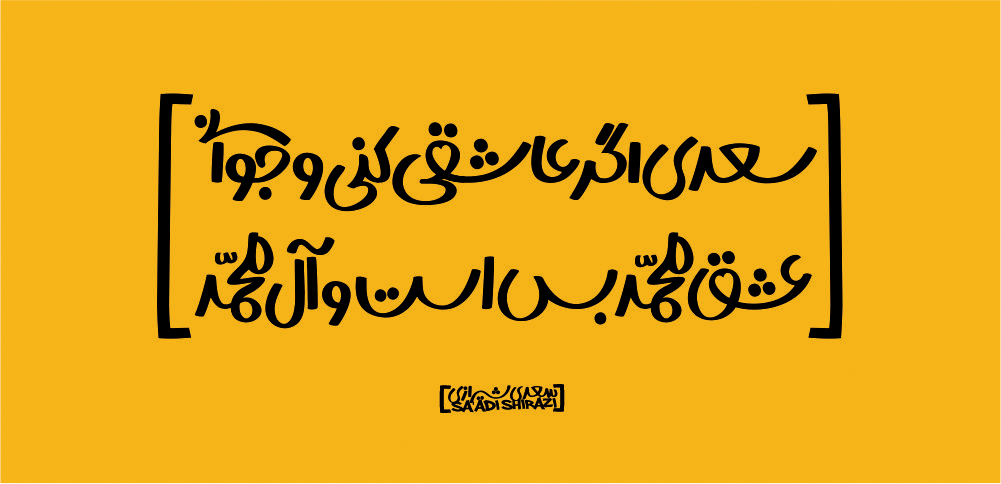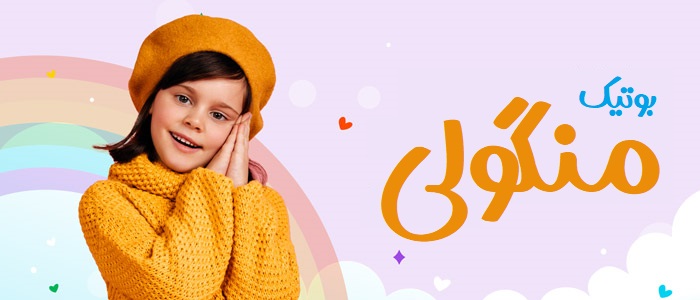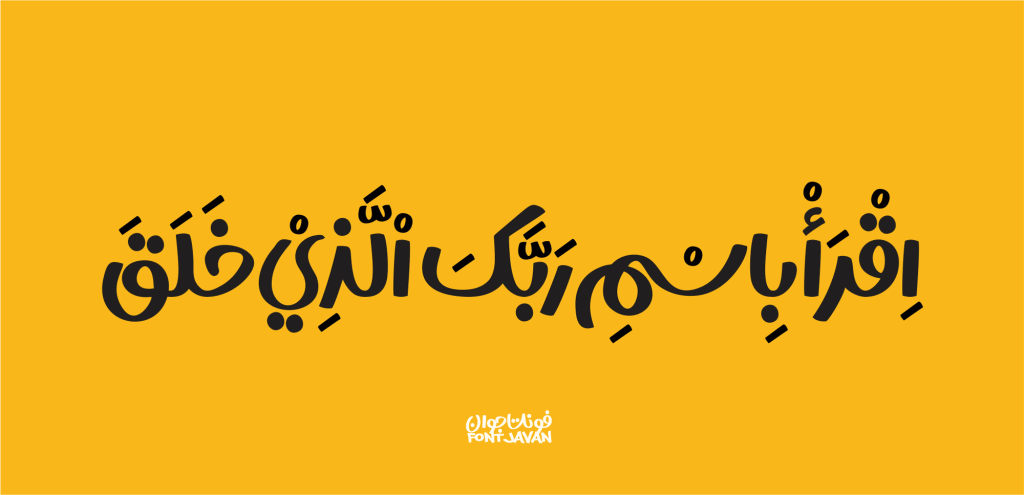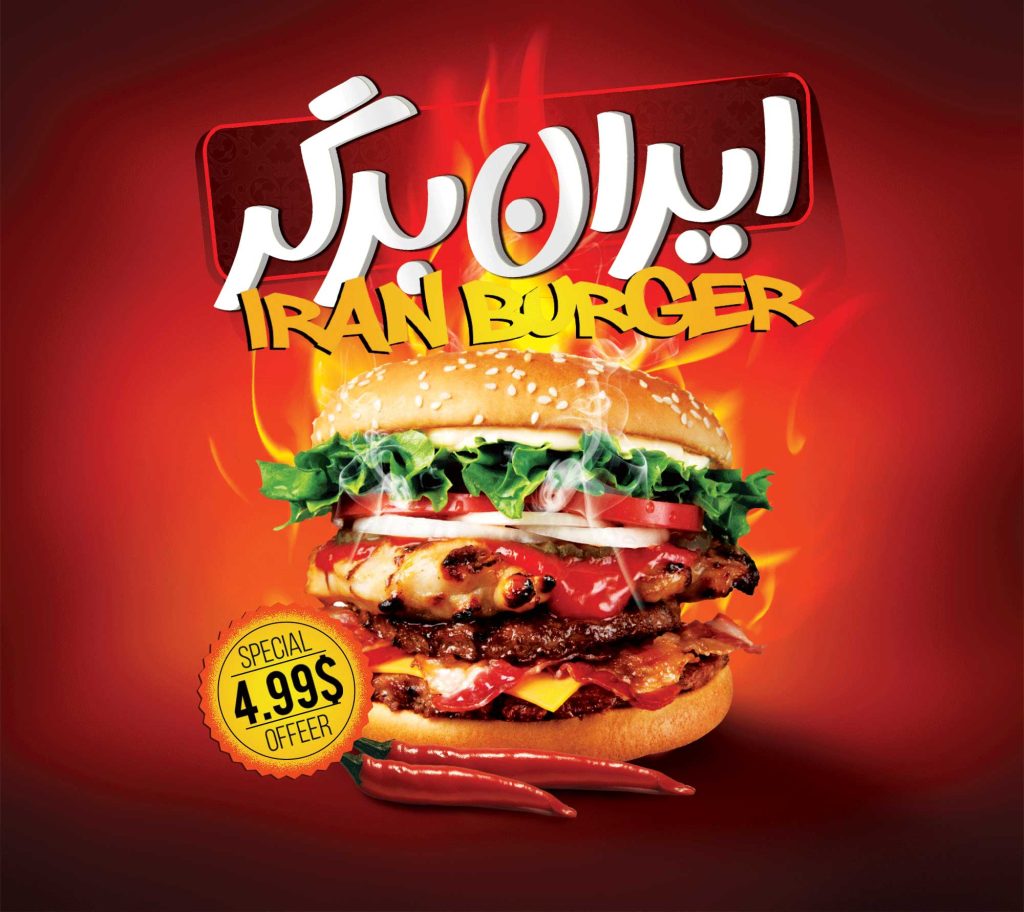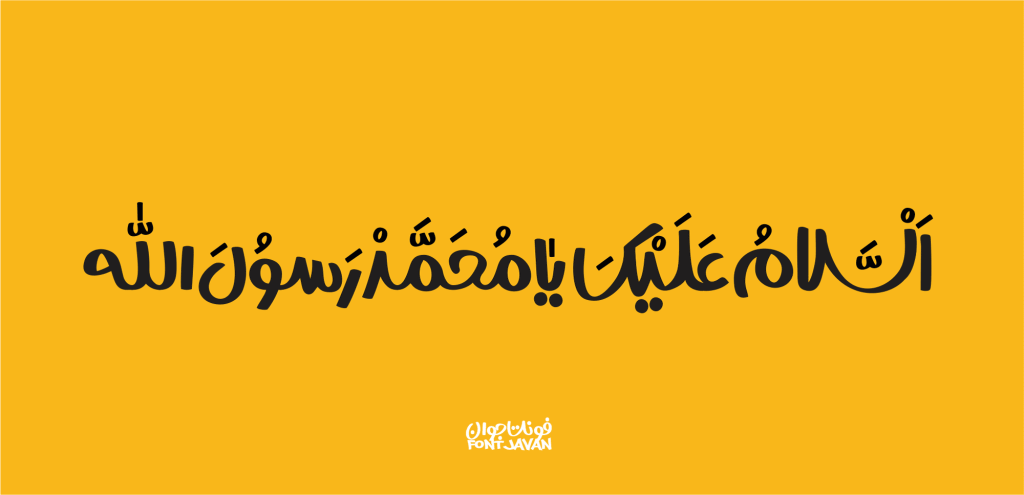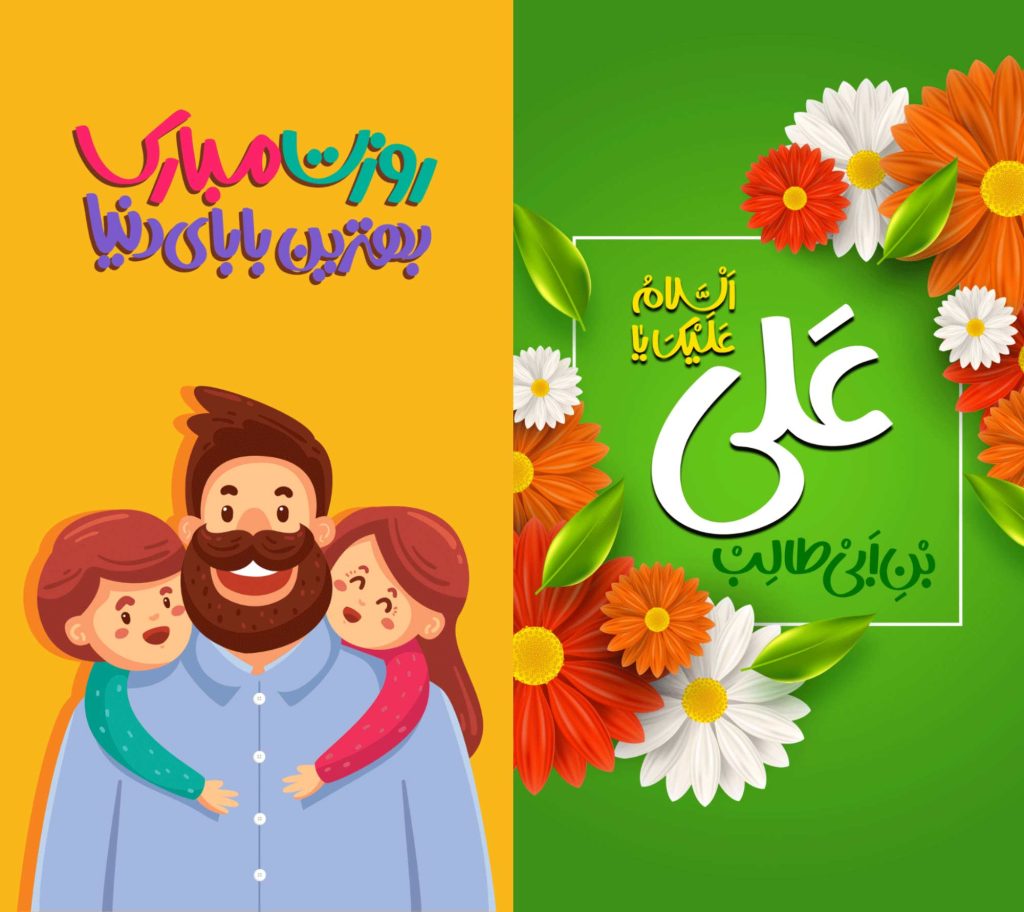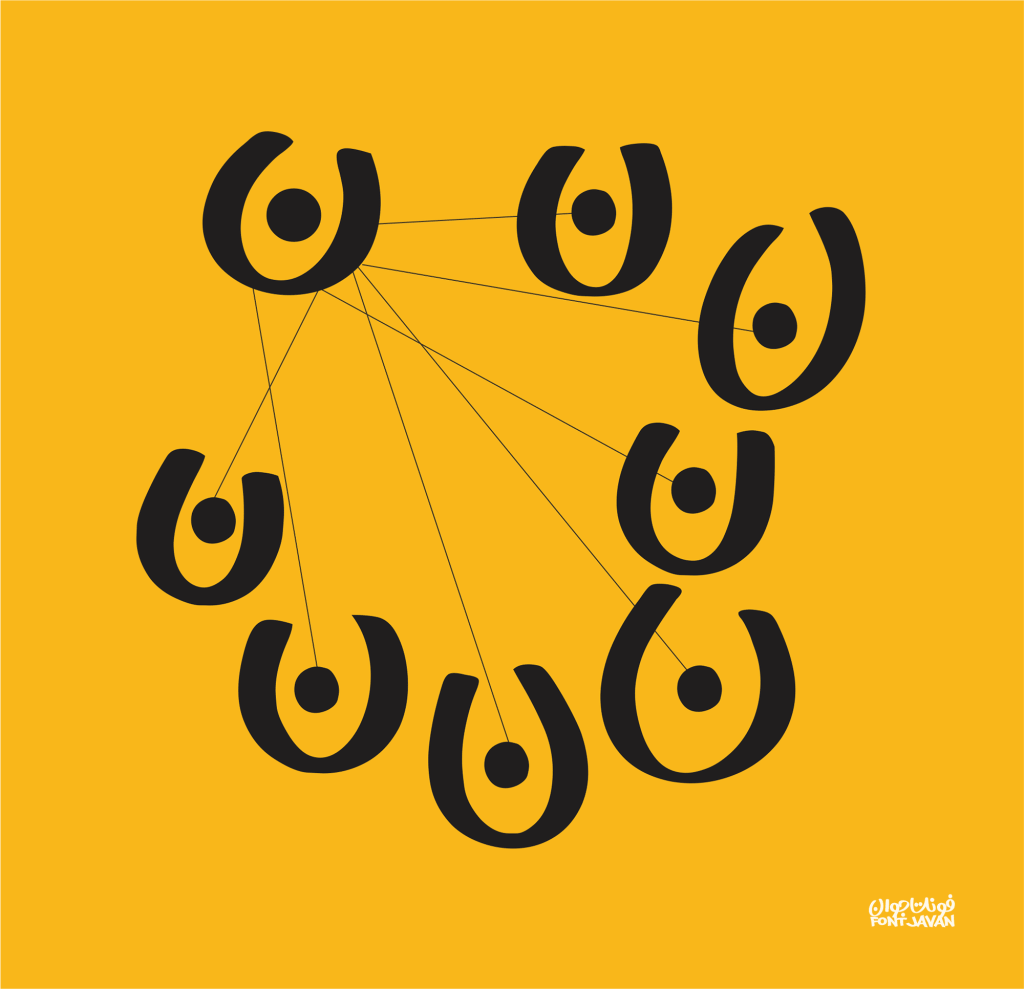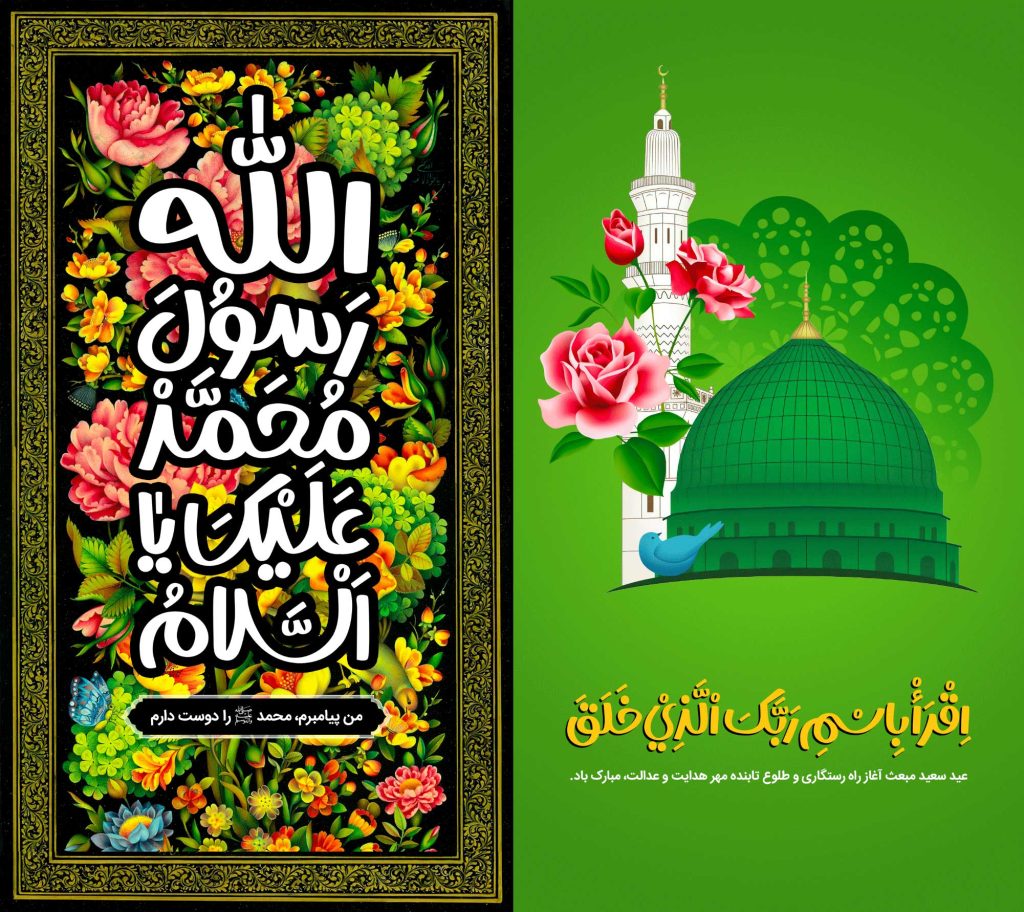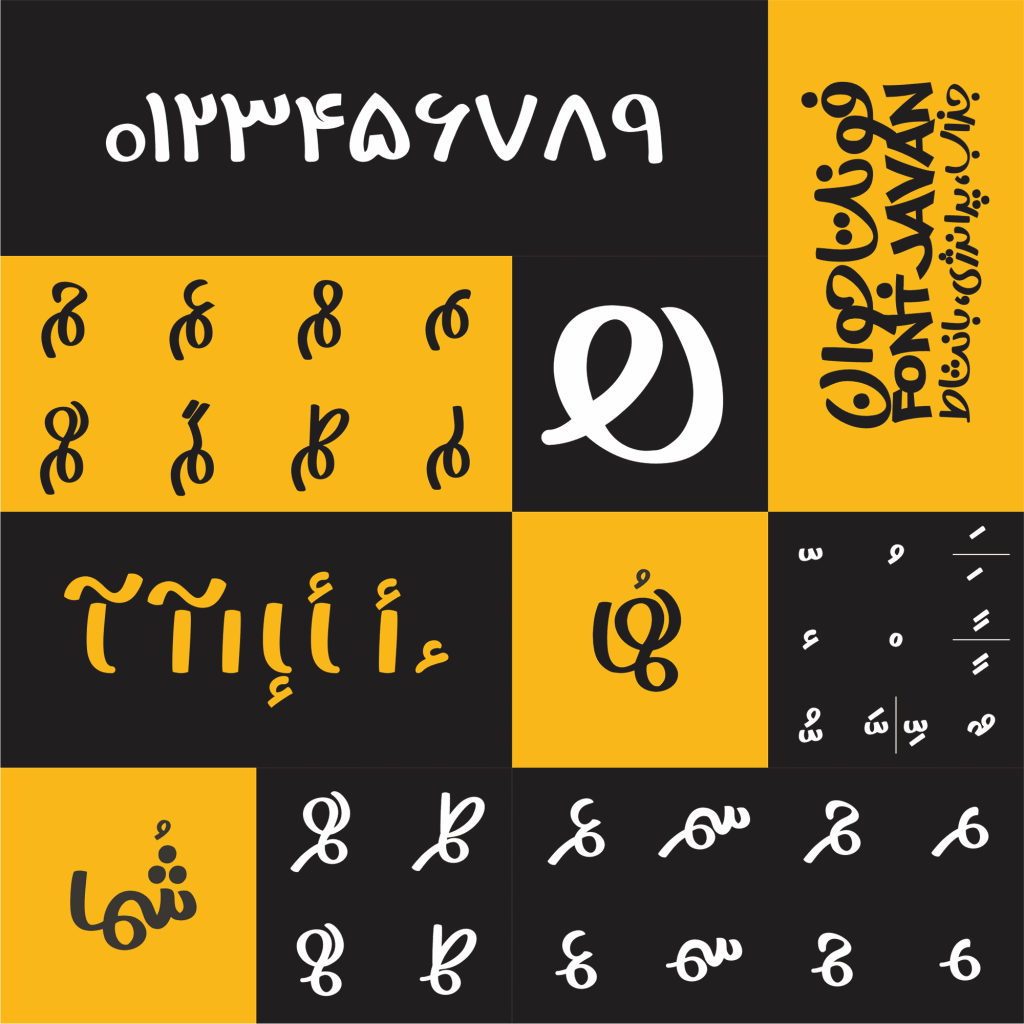
فونت جوان
فونت جوان قلمی دست نویس دارای ویژگی نمایشی می باشد. اگر به دنبال جذب مخاطبین و خوانندگان در عناوین ، پوستر های تبلیغاتی ، بنر ها و … هستید بی شک جوان با شور و اشتیاق و رابطه صمیمی که با نگاه مخاطبین خود برقرار می کند انتخابی بی نظیر می باشد .
جوان نتیجه تلاش ها و زحمات قاسم نجاری طراح آن می باشد. وی از متخصصین ساخت این دسته از تایپ فیس های زیبا و پر تحرک است. او پیش از این فونت های آوینی و کتیبه را در وبسایت فونتایران مرجع رسمی فروش قانونی و آپدیت انواع تایپ فیس های فارسی منتشر کرده بود که هر دو از فونتهای بسیار پرطرفدار و پرفروش هستند.
می توان با اطمینان به این نکته اشاره کرد که قلم ماژیکی خصوصیت اصلی استفاده شده در جوان که از دستخطهای نوشته شده با ماژیک در بعضی آثار گرافیکی و امضاهای گرافیتی اقتباس گرفته شده است.
پشتیبانی از حروف جایگزین متنوع
در این تایپ فیس تعداد بسیار زیادی حروف و ترکیبات جایگزین است که با بهره گیری از فایل راهنمای آن میتوانید آنها را تایپ کنید و به تایپوگرافی دلخواه و مدنظر و سفارشی خویش دست پیدا کنید.
این قلم شخصیت همانند نام خود دارد پرانرژی و پویاست. ارتباط نزدیک و صمیمی که با مخاطبین خود برقرار می کند دلیلی محکم جهت انتخاب علاقه مندان به این تایپ فیس می باشد. در زیر تصاویر مربوط به این قلم زیبا را مشاهده می نمائید.